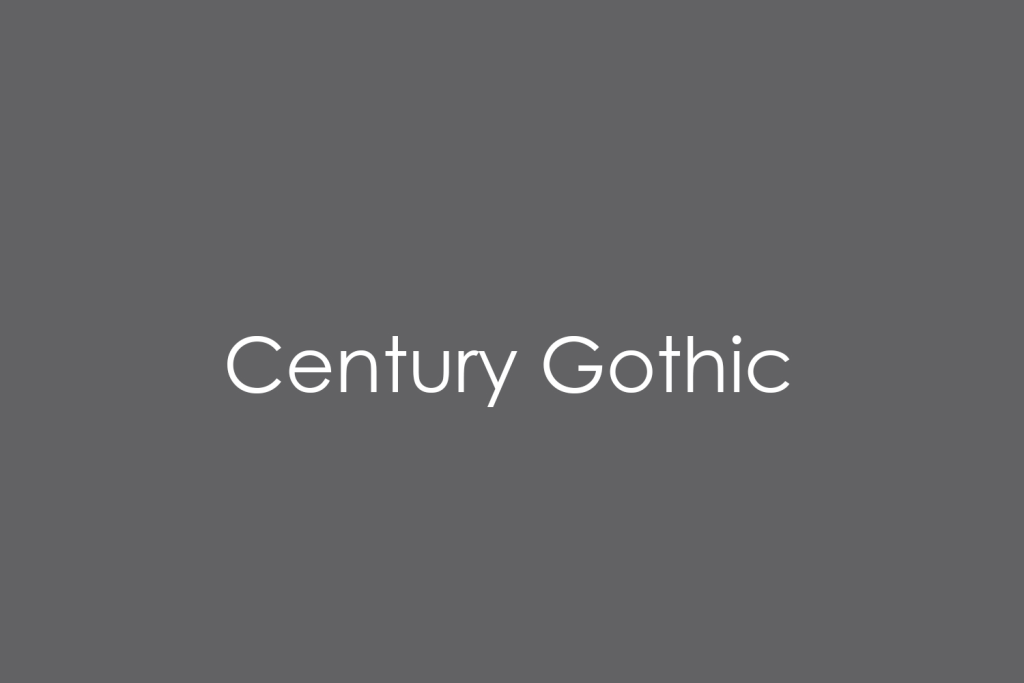
Century Gothic Font
Tác giả: Monotype Imaging
Ngày phát hành: 1991
Bộ Font: Century
Phân loại: Hiện đại
Độ dày: Regular, Bold
Century Gothic Font nổi bật với các đường nét gọn gàng, hình dạng chữ tròn trịa và độ dày đồng đều, tạo nên một vẻ ngoài tinh tế và đơn giản. Nhờ sự kết hợp hoàn hảo giữa tính thẩm mỹ và chức năng, mẫu font này thường được sử dụng rộng rãi trong thiết kế quảng cáo, in ấn và các tài liệu kỹ thuật số. Đặc biệt, Century Gothic Font rất phù hợp cho việc sử dụng trong các tiêu đề và văn bản ngắn, giúp thu hút sự chú ý của người đọc một cách nhanh chóng. Với vẻ ngoài hiện đại và chuyên nghiệp, Century Gothic Font tiếp tục là lựa chọn ưa thích của các nhà thiết kế đồ họa khi tìm kiếm một mẫu font chữ không chân có sức hút mạnh mẽ.